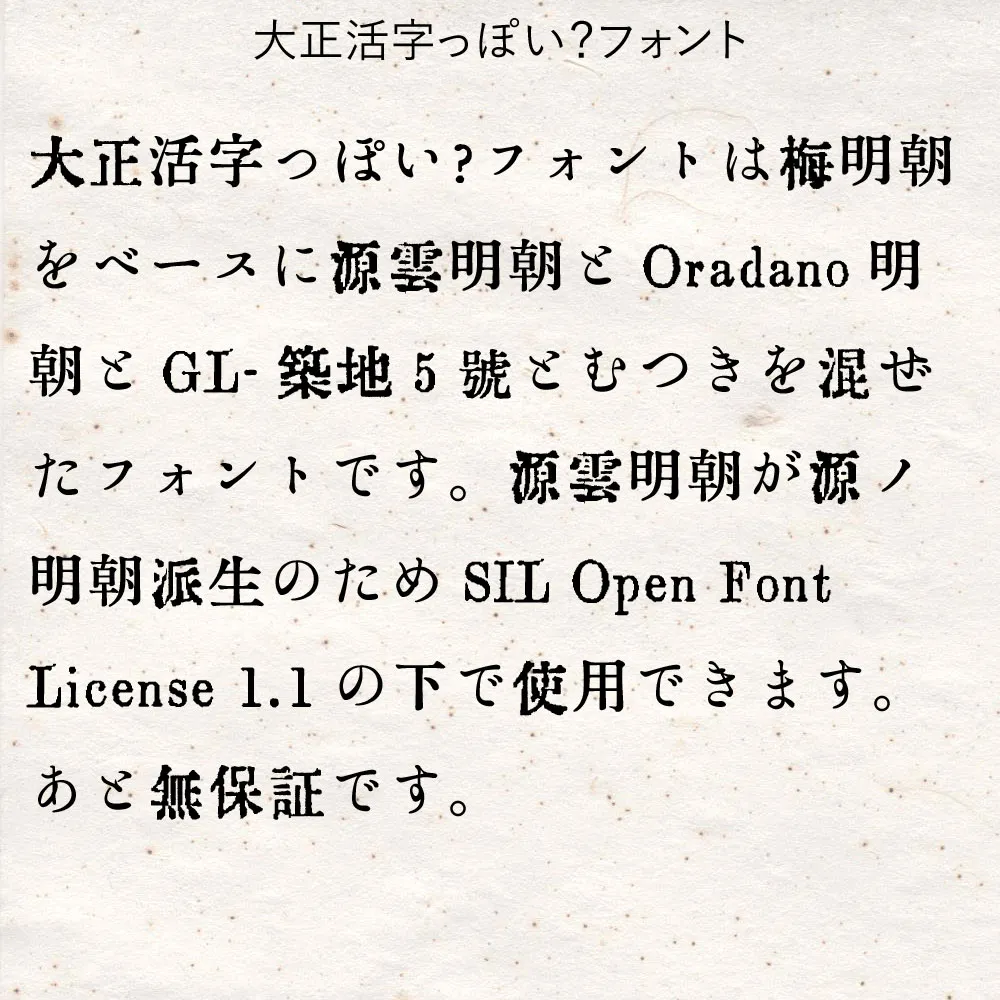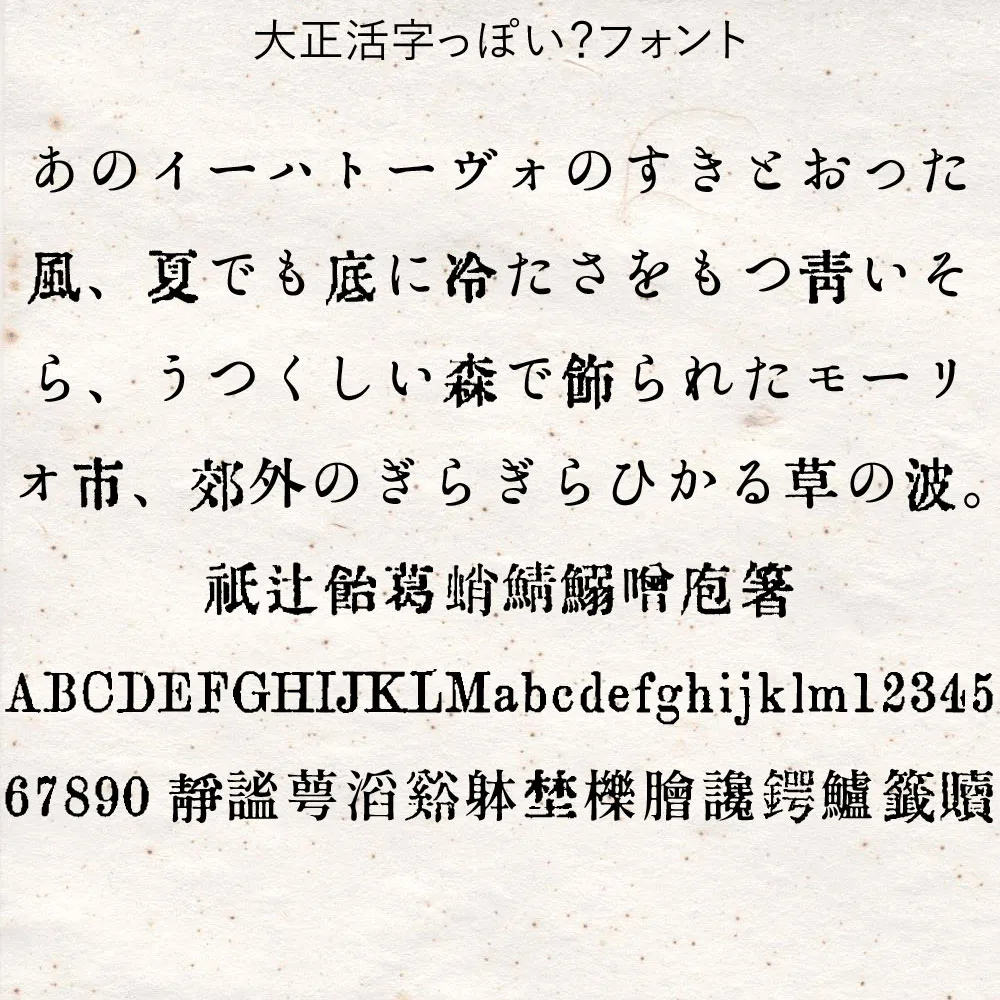
像大正活字嗎?以梅明朝為基礎,混合了源雲明朝和Oradano明朝和GL-築地5號和木結的字體。
大正活字っぽい?フォントは梅明朝をベースに源雲明朝とOradano明朝とGL-築地5號とむつきを混ぜたフォントです。源雲明朝が源ノ明朝派生のためSIL Open Font License 1.1の下で使用できます。あと無保証です。